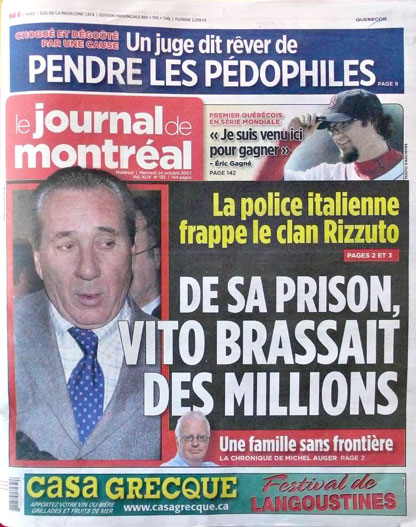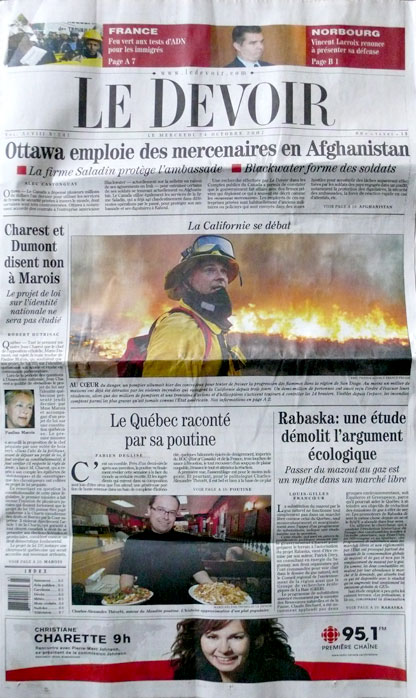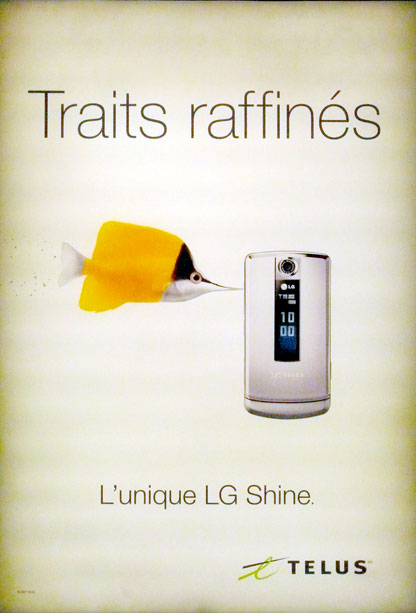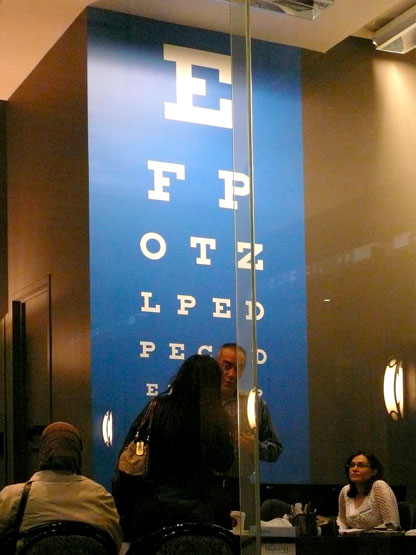
pendant ce temps le feu grondait en Californie et je re-découvre le format des journaux de Montréal… cathédralesque.
les journaux sont vraiment épais…
Me suis amusé à décrypter cette affiche et surtout la faute d’orthographe trop évidente pour ne pas être voulue… Alors vous êtes toujours effrayé (vous le lecteur de l’affiche), par les mulots, ou bien par cette femme hystérique? et si personne n’avait vue la faute… et si c’était un travesti?… un chose est sûr la modernité au Québec n’a pas le même sens que pour nous… Les téléphones et autres appareils gadgets ne sont pas du dernier cri, Nikon n’a pas encore introduit le D300 ni le D3 sur le marché Québécois bref… ce n’est pas vraiment une grande angoisse ici que de ne pas être au top du top des geeks.
Des tabloïds francophones et anglophones… pour moitié à la louche, la communauté de Montréal parle l’une ou l’autre langue.
L’humour légendaire des québécois
L’Helvetica, toujours à la mode, pour combien de temps…? bientôt les graphistes vont redécouvrir les vertus du Futura de Paul Renner. La mode en typo ça va ça vient, aussi…
Un panneau d’ophtalmologue chez un opticien du centre commercial… Une anecdote aussi… un jour, lors de l’inauguration d’un Salon des Artistes Décorateurs au Grand Palais (SAD), André Malraux s’arrête devant une affiche de Roger Excoffon qui représentait l’alphabet Antique Olive…«c’est intéressant cette affiche pour ophtalmologue…» nous dit le ministre de la culture Malraux… on comprend mieux l’indigeance de la typographie française vue par les «officiels» encore aujourd’hui.
J’avais oublié combien on aimait la typographie à Montréal… mais ça me rappelle mes discours sur les différences culturels concernant la typo entre pays catholiques et protestants ou anglicans… Théorie que je ne cesse d’égrener sur D&T depuis deux ans.
La rue est support typographique ou n’est pas… La typo est partout et participe du paysage urbain…